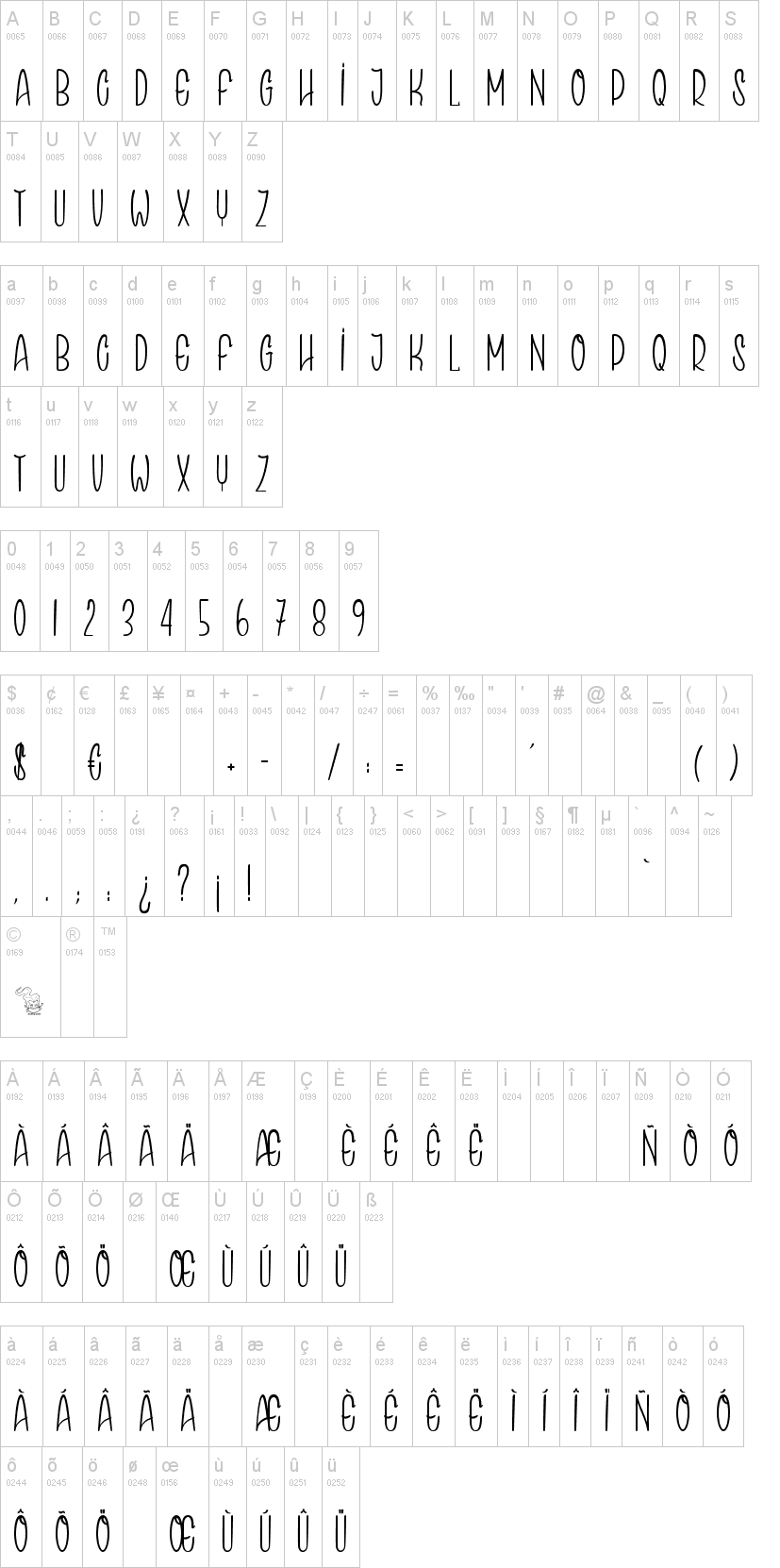
Speak Easy
Speak Easy是一款精致而现代的字体,由英国设计师Gemma O'Brien创作,它具有温暖的质感,更具有独特的视觉效果,能够提升文字的视觉效果,同时也能够增加更多的情感色彩。它的字体结构清晰,可以很好地表达文字的内涵,而且它的字体图案也非常独特,具有抽象的艺术感,能够更好地提升文字的美感。
Speak Easy是一款非常不错的手写艺术字体,具有很好的视觉感,适合于文化类的宣传设计、商业类品牌的广告和产品包装设计以及个性化文字排版等较多场景。